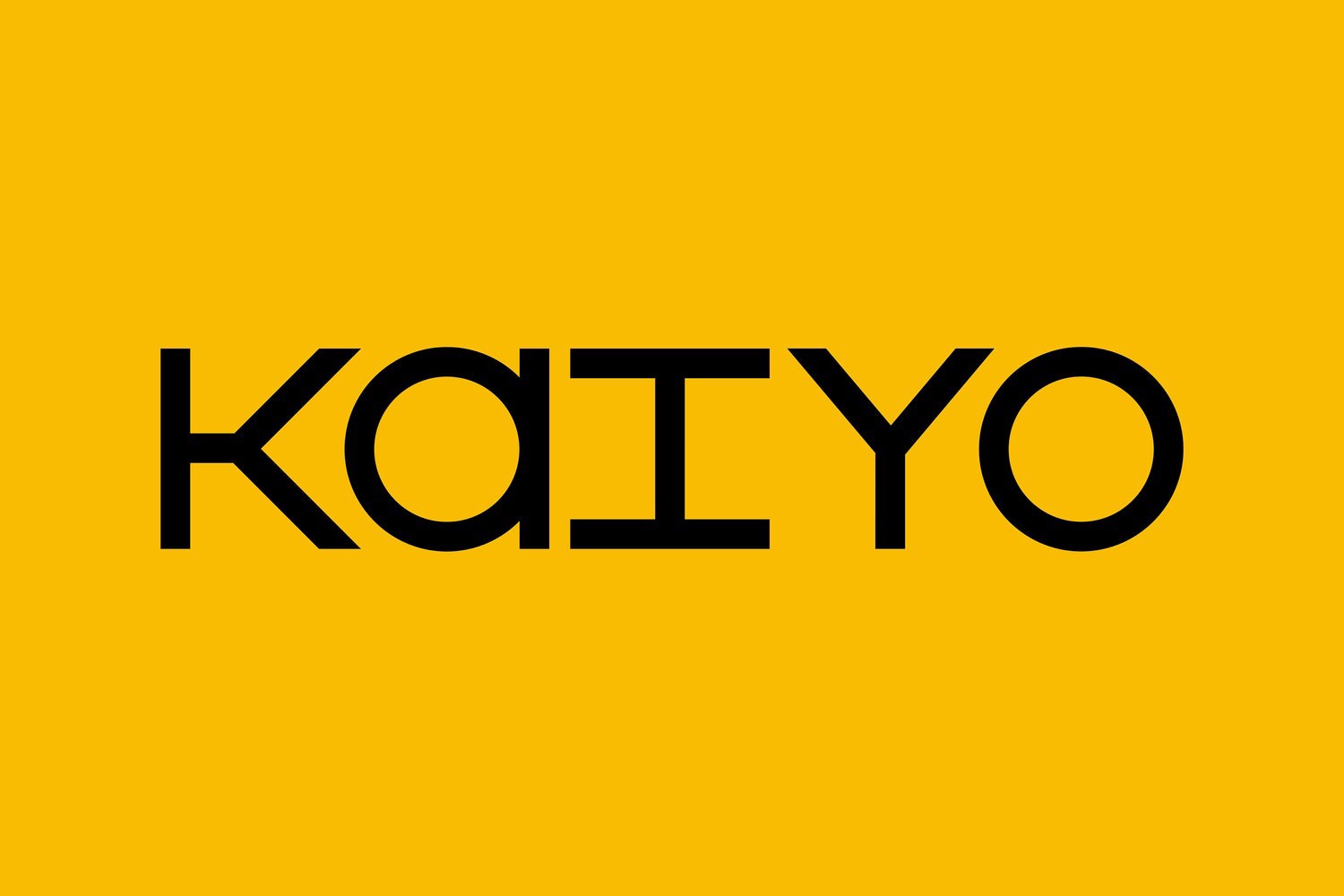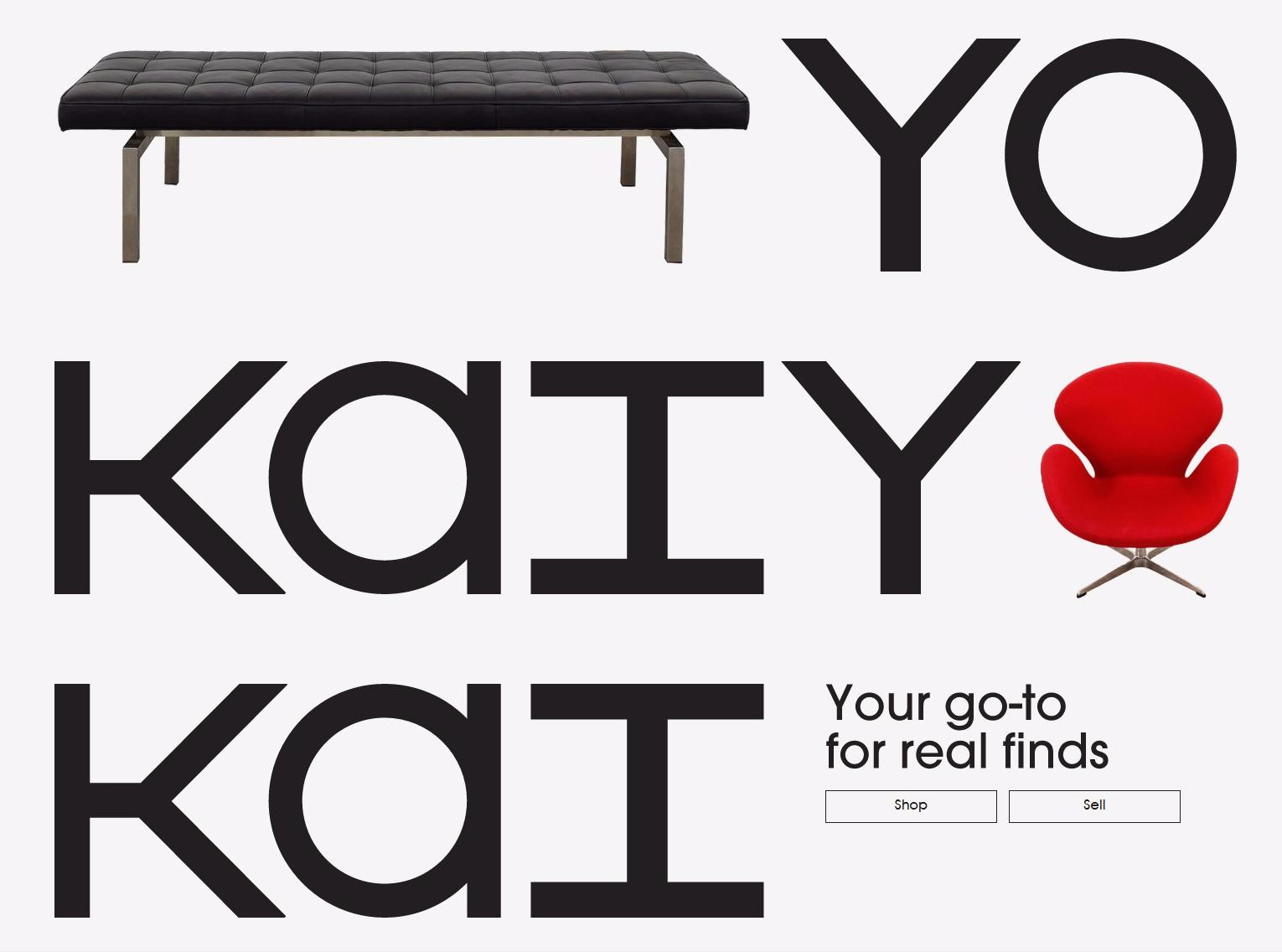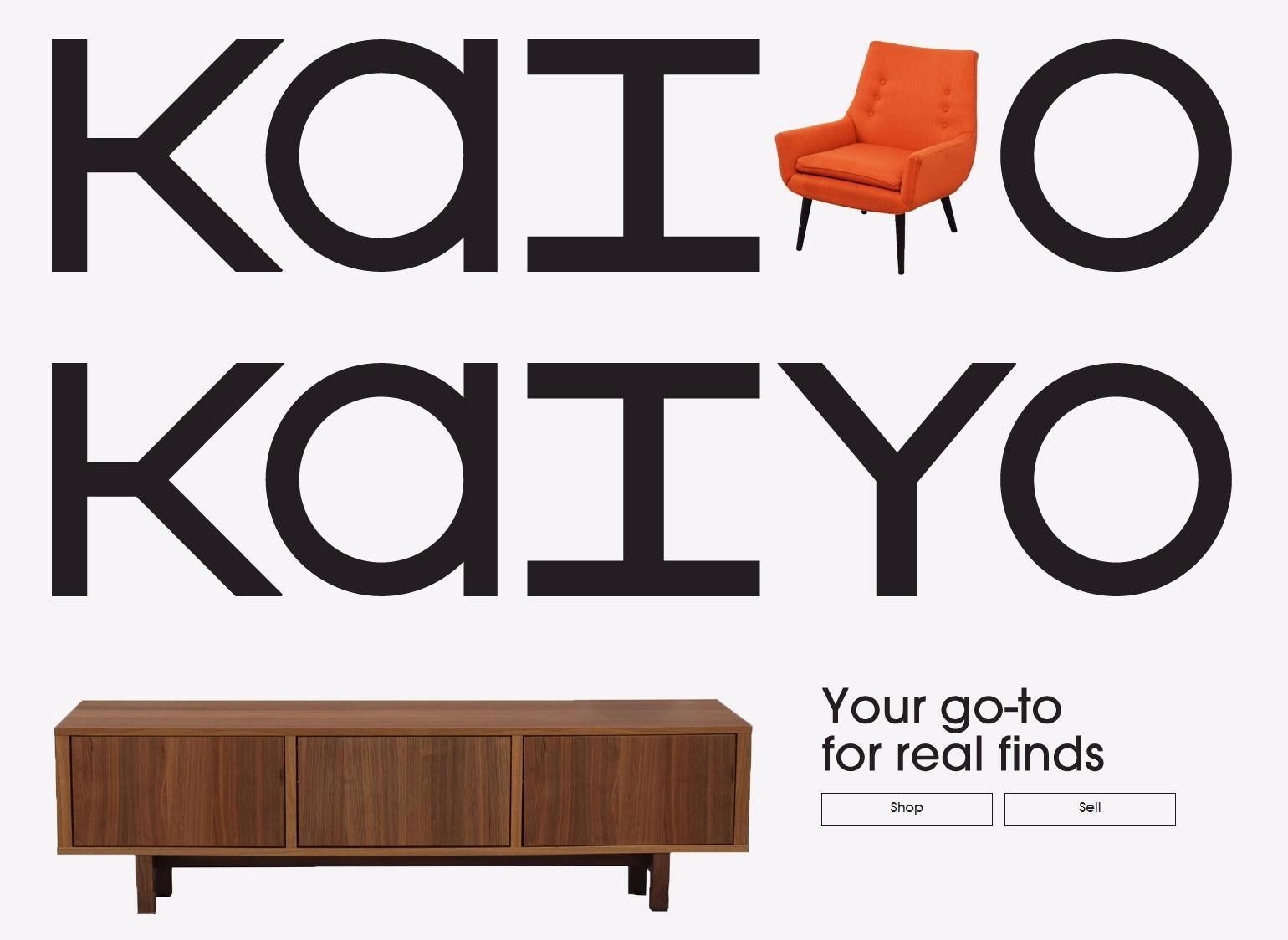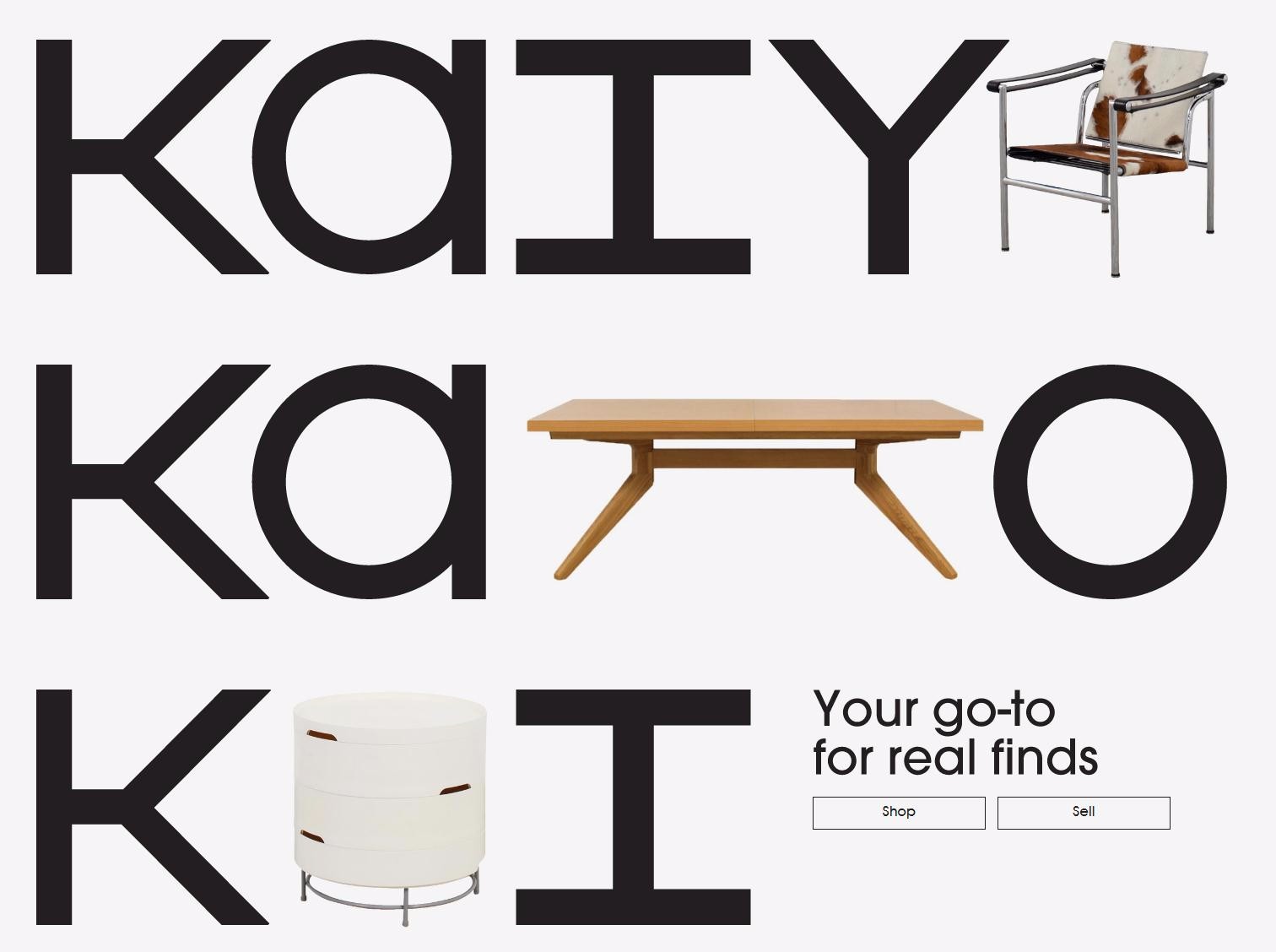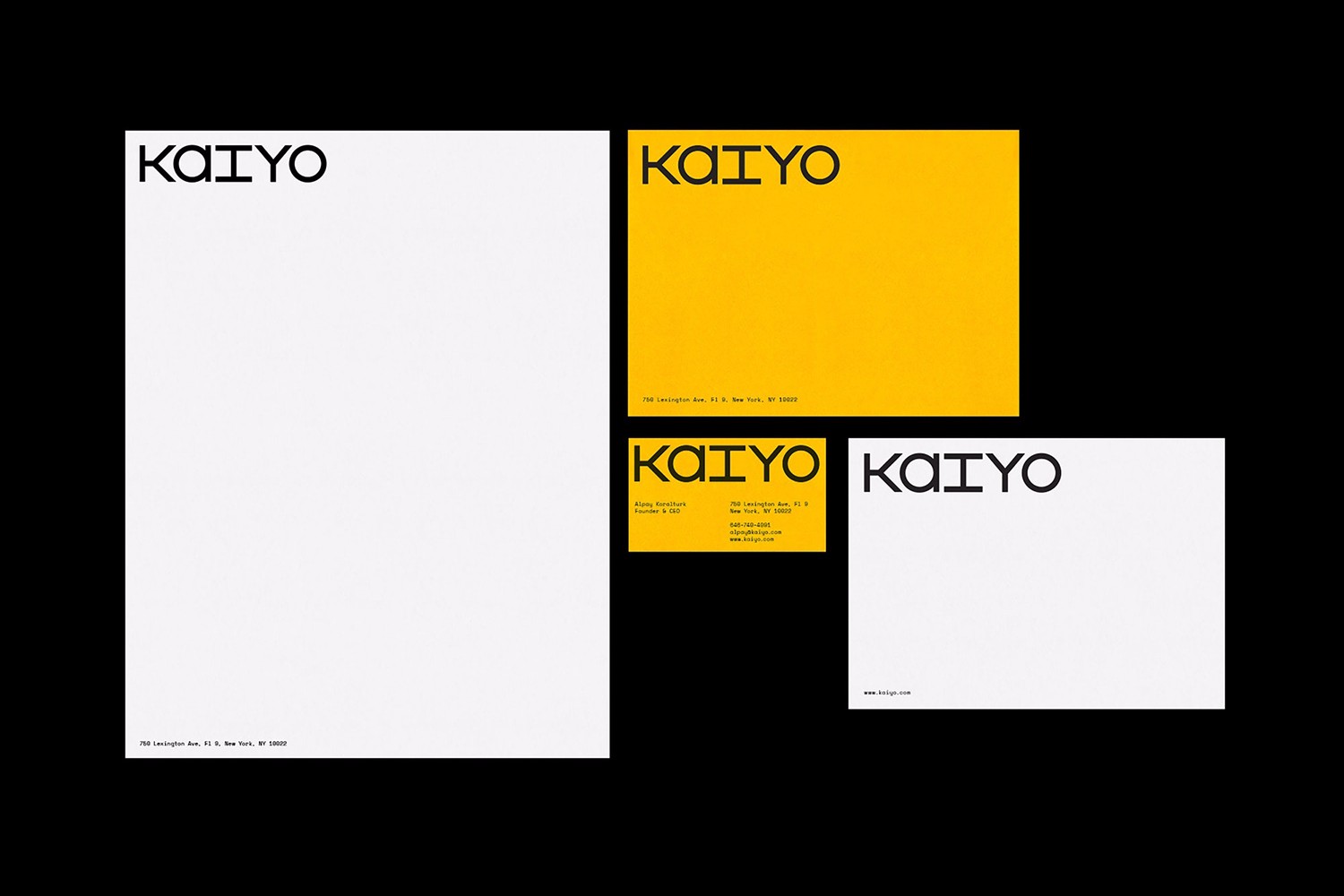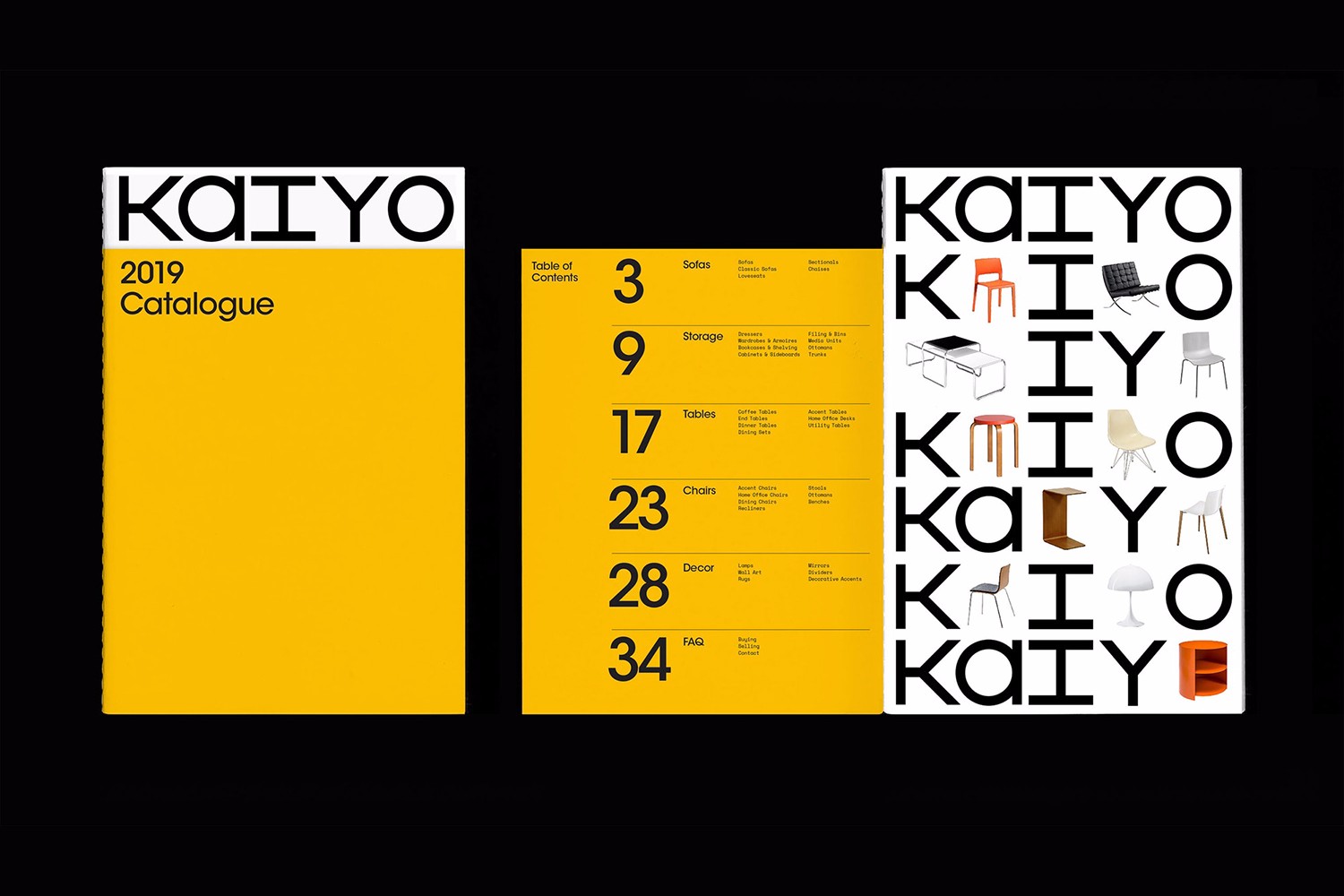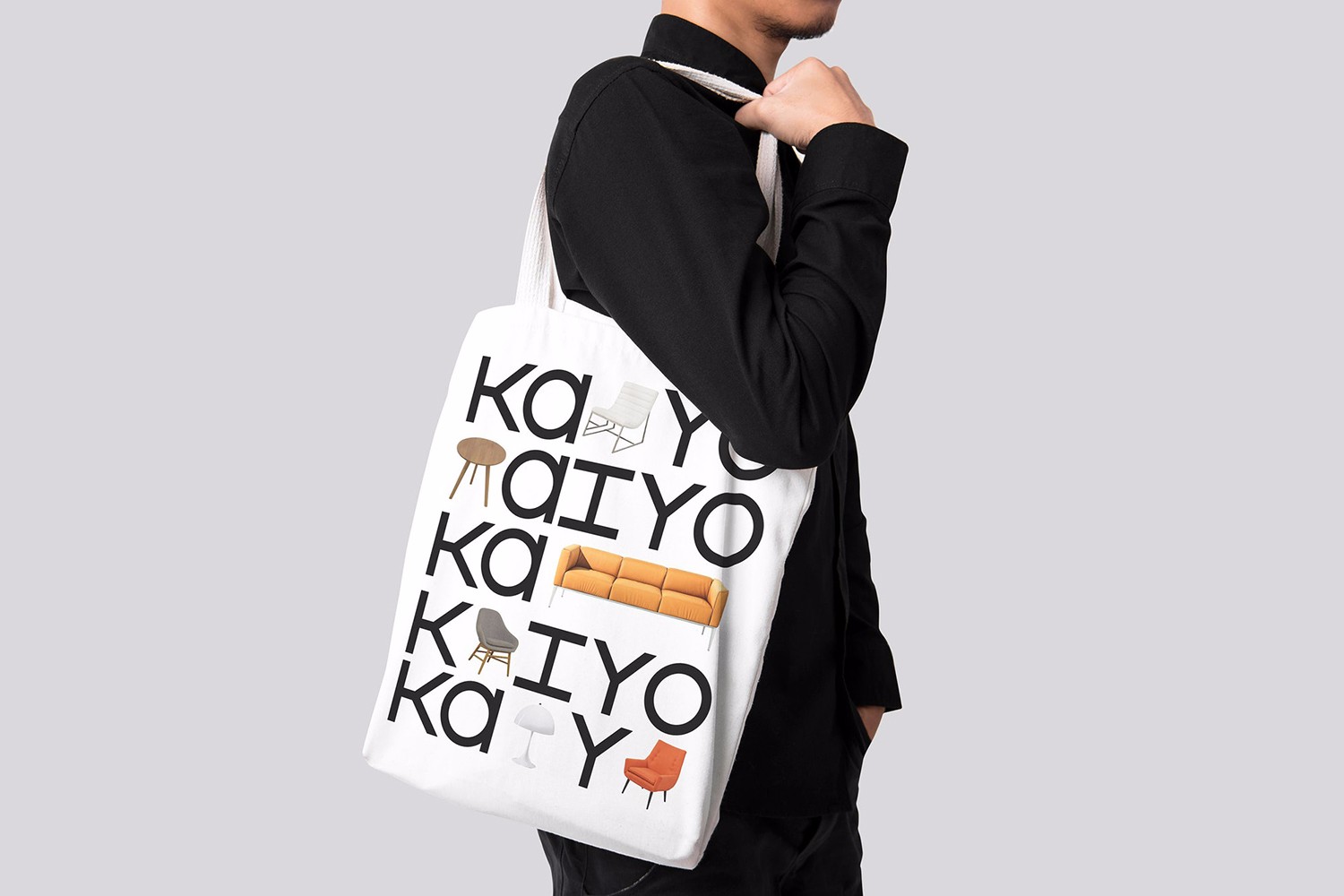
这个二手家具的品牌形象设计,你也可以学学
Kaiyo前身为Furnishare,是一家在线转售和购买二手家具的平台。目前,Kaiyo在纽约市和新泽西州营业,并有意向全球扩张。
Kaiyo支持在线提取、检查、清理、拍摄和上传家具图片,大大减轻了二手家具在线销售的困难。它是日益增长的回收运动的一部分,挑战着大型家具零售商的季节性促销,要知道在美国,每年大约800万吨家具进入垃圾填埋场。Kaiyo定位的核心是:现代生态主义、适合每个人的好设计、重复使用和耐用。
这是由五角设计公司Natasha Jen的设计团队设计的,包括命名、图形标识,以及延伸的网站、宣传册、送货车、手提袋和封箱带等。
时代精神、升级回收、耐用和可重复使用被称为现代优秀设计原则。目前为止,二手的生意都是在个人基础上进行管理,如克雷格分类广告(Craiglist)、Ebay、二手市场、二手商店等,五角设计为二手世界带来了更高级别的零售品质。
将图像置于字体中是设计中的经典,这建立了一种直接沟通的视觉语言。这种方法生成引人注目的设计,执行却非常简单:单人、双人或三人沙发,长或短梳妆台,小咖啡桌或灯,都非常恰当地落入到网格中,与一个或两个等宽的字符空间相当。
这样的品牌设计有着特别的意义,连续的、模块化的呈现方式,字体可以与各种二手产品组合在一起,乱中有序,这与之前那些用户生成的平台完全不同。
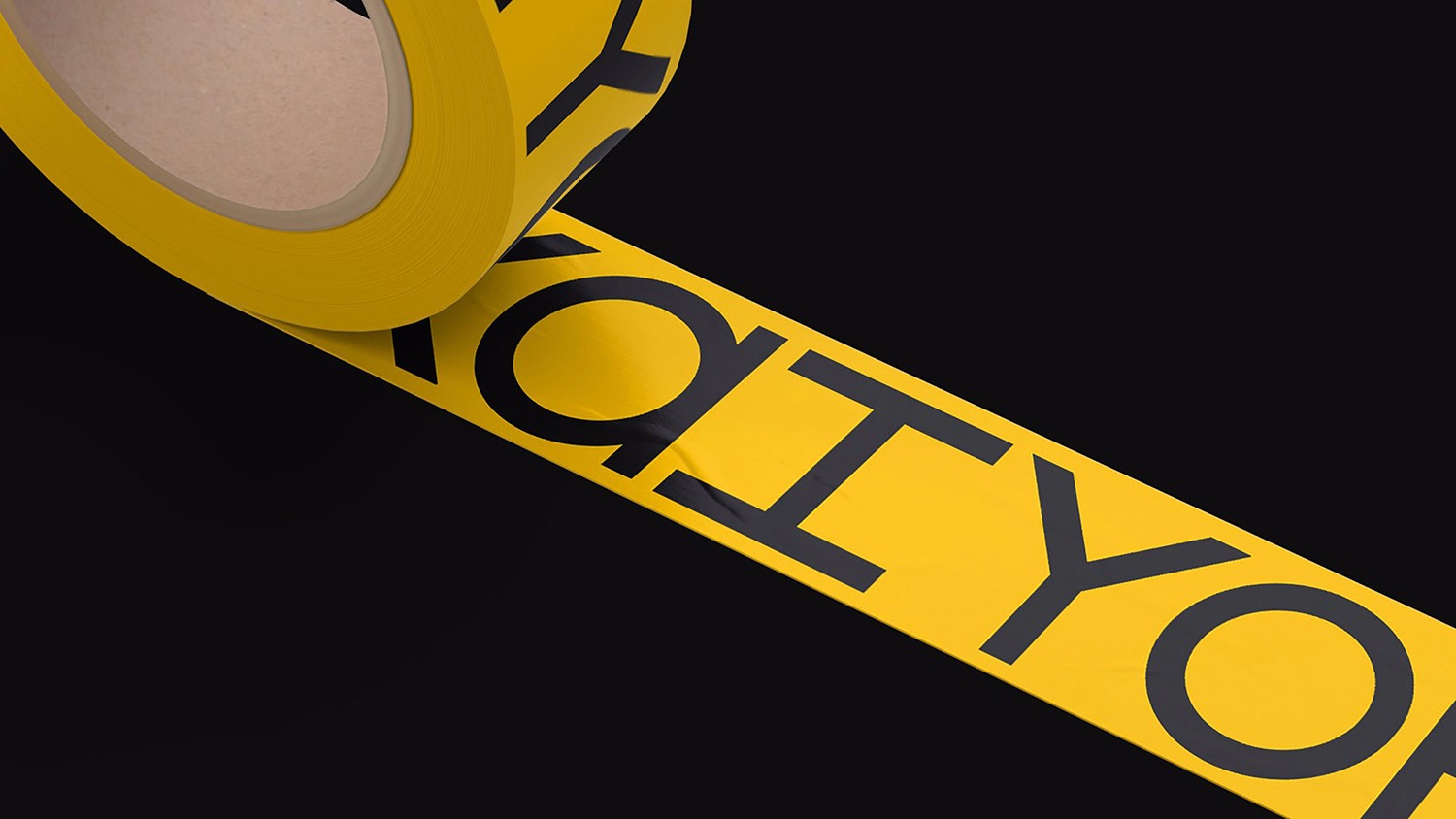
设计:五角设计公司
设计师:Natasha Jen设计团队
概念:Richard Baird
字体:Avant Garde Gothic、Space Mono